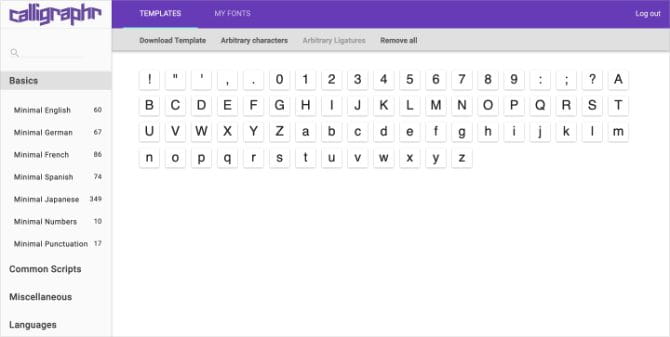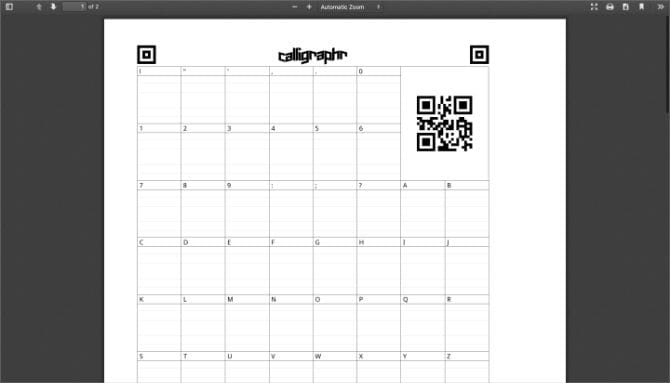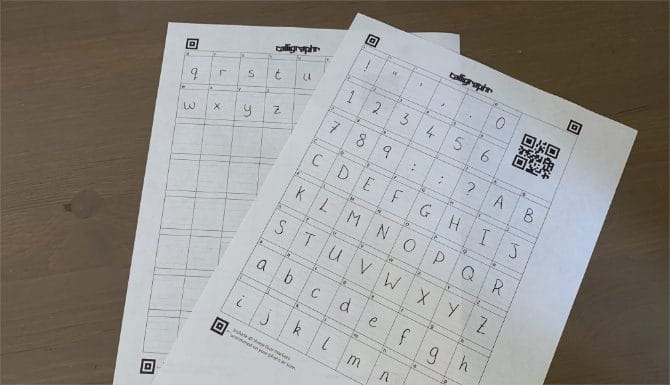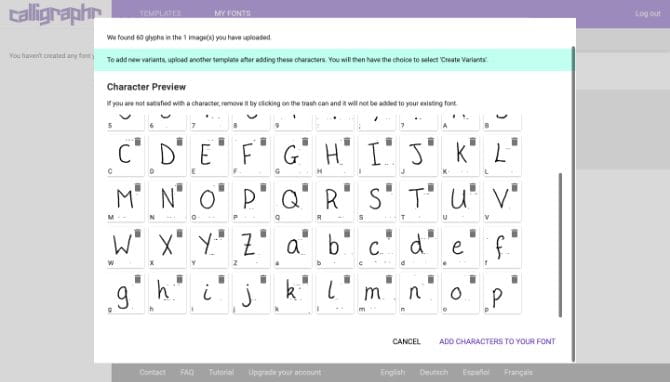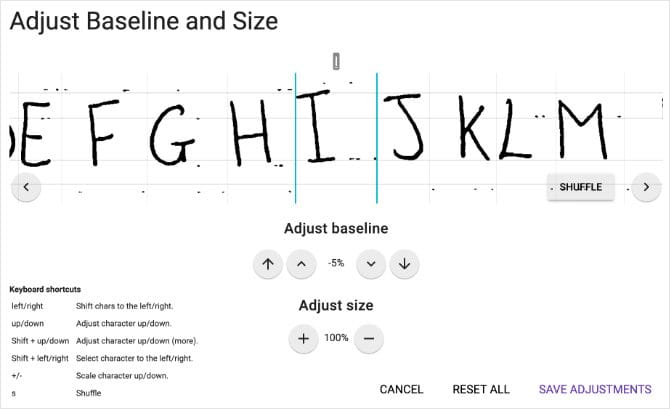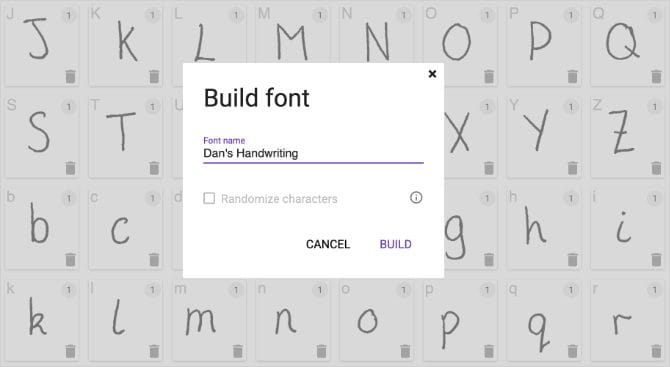
sta creando linea di lettere utilizzando grafia Un modo innovativo per creare personaggi e documenti unici sul tuo computer. Puoi scrivere e stampare lettere e parole usando la scrittura a mano come una lettera Per aggiungere un tocco personale.
Così puoi aggiungere un tocco unico ai tuoi progetti digitali convertendo la tua calligrafia in un font personalizzato. Farlo è molto più semplice di quanto potresti pensare grazie a un'app Web chiamata Calligraphr. Molti usi creativi per esplorarlo.
In questo articolo, ti mostreremo come creare gratuitamente la tua calligrafia con Calligraphr. Puoi aggiungere varianti di carattere per lo stile naturale, regolare l'allineamento e la spaziatura e persino esportare il prodotto finale come formato di carattere standard. Ci vogliono solo dieci minuti.
Cos'è Calligraphr?
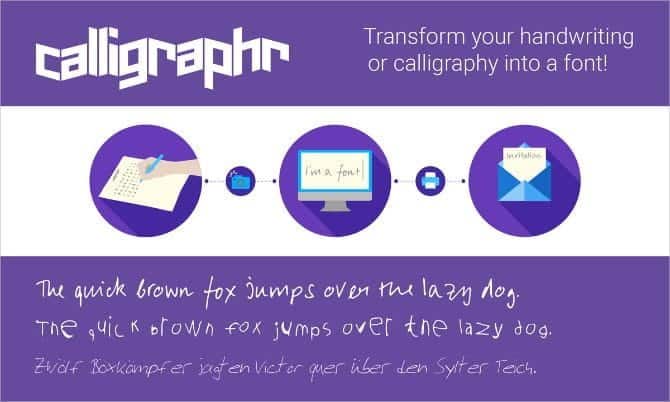
Precedentemente noto come MyScriptFont, Calligraphr è un'applicazione web gratuita che ti consente di scansionare la tua grafia per creare caratteri personalizzati. È facile da usare e offre molte funzionalità che ti aiutano a ottenere il tuo carattere giusto.
Puoi quindi esportare il carattere personalizzato in formato TTF o OTF per l'uso su computer Windows o macOS. Potresti voler utilizzare il tuo carattere personalizzato per aggiungere un tocco personale agli inviti, progettare opere d'arte con la tua grafia o per scrivere contenuti web.
Calligraphr offre le seguenti funzionalità per aiutarti a perfezionare la creazione di caratteri personalizzati:
- Scegli i set di caratteri esatti che desideri includere nel tuo font, inclusi lettere, simboli e numeri.
- Carica variabili per ogni lettera per creare credibilità casuale per la tua calligrafia.
- Modifica i singoli caratteri dopo il caricamento per scurire il carattere, regolare le dimensioni e regolare l'allineamento.
- Salva i caratteri nel browser in modo da poter tornare a continuare a modificarli attraverso più sessioni.
Puoi anche aggiungere più di 15 variabili per carattere, fino a un massimo di XNUMX caratteri. Un carattere alternativo è una versione alternativa di una particolare lettera o numero. Il carattere finale utilizza diverse variabili casuali per rendere il carattere più naturale.
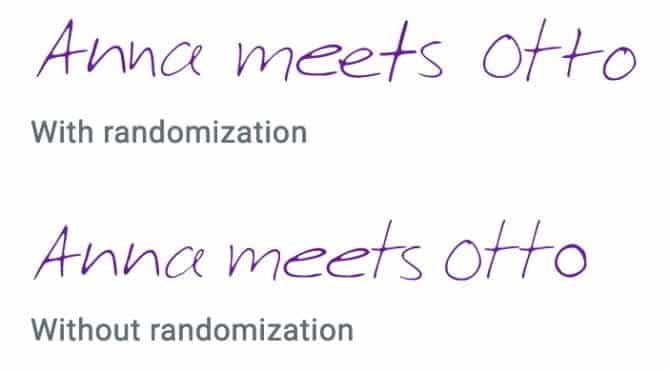
Un altro importante aggiornamento che ottieni con un abbonamento Pro è la possibilità di aggiungere collegamenti alfabetici al tuo carattere. Se non hai familiarità con il gergo tipografico comune, una legatura è una linea che collega due caratteri con una grafia correlata (un simbolo risultante dall'unione di due o più simboli o due o più caratteri per formare un'uniforme che esprime i due simboli insieme).
Infine, non puoi aggiungere collegamenti alfabetici utilizzando l'opzione gratuita di Calligraphr. Ma se non stai comunque collegando i caratteri nella tua calligrafia, non farà differenza.
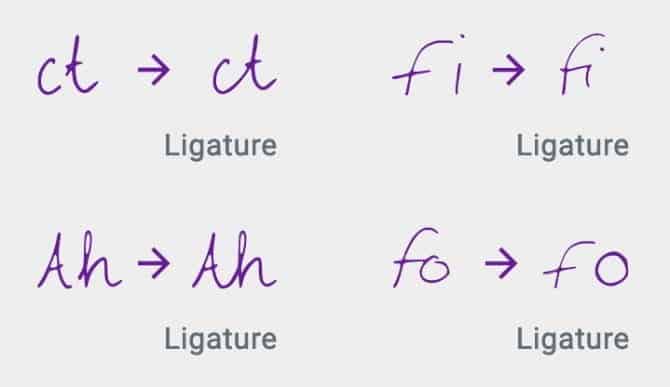
Come utilizzare Calligraphr per trasformare la tua calligrafia in caratteri personalizzati
Per iniziare, vai al sito calligrafo e fare clic sul pulsante Inizia gratuitamente Per creare un account. Non è necessario eseguire l'upgrade a un account Pro a meno che non si desiderino più di due varianti di un singolo carattere o connessioni alfanumeriche.
Dopo esserti registrato e aver effettuato l'accesso, fai clic sul pulsante Avvia l'app Scarica l'app Web Calligraphr. Quindi segui i passaggi seguenti per convertire una linea la tua calligrafia a una linea di lettere dedicata.
Passaggio 1. Crea un modello di carattere
Per prima cosa devi creare un modello per il tuo carattere personalizzato. Questa è fondamentalmente una griglia di quadrati con un quadrato per ogni lettera che vuoi includere nel tuo carattere. Dopo aver creato e stampato il modulo, è necessario digitare manualmente ogni lettera nelle caselle. Quindi scansiona di nuovo il modulo sul tuo computer per creare il carattere personalizzato.
Ottieni più font gratuiti da aggiungere alla tua raccolta
Ora sai come rendere la tua calligrafia una scritta personalizzata. Usalo per personalizzare tutto da inviti di nozze ai biglietti da visita. Ma non sentirti in dovere di usarlo su tutto.